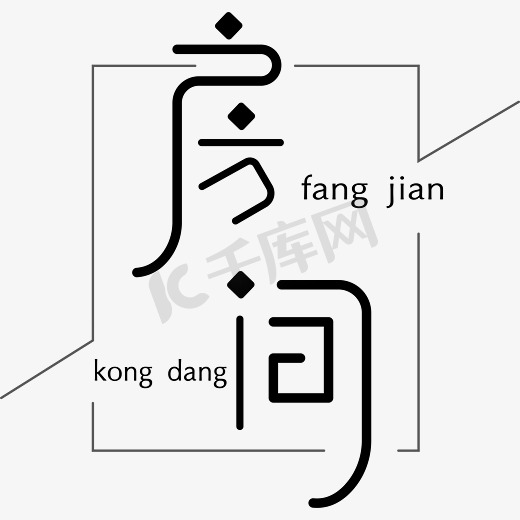
字体在室内设计中的作用:提升空间的氛围 (字体在室内设计图片)
提升空间的氛围
字体不仅是文字的载体,在室内设计中,它也是一种重要的设计元素。巧妙运用字体,可以创造出不同的空间氛围,提升整体空间的美感和品味。
字体的选择
在选择字体时,需要考虑多种因素,包括:
• 空间的风格:不同的空间风格有不同的字体选择,例如,现代风格适合简约的字体,而古典风格则需要更加华丽的字体。
• 空间的功能:不同功能的空间需要不同的字体选择,例如,卧室可以使用舒缓的字体,而办公室则可以使用明快的字体。
• 空间的大小:小空间适合使用小字体,而大空间则可以使用大字体。
• 字体的可读性:字体需要清晰易读,尤其是当它用于标牌或墙面装饰时。
字体的排版
字体的排版也很重要。合理的排版可以提升字体的可读性和美感。排版时需要注意以下几点: